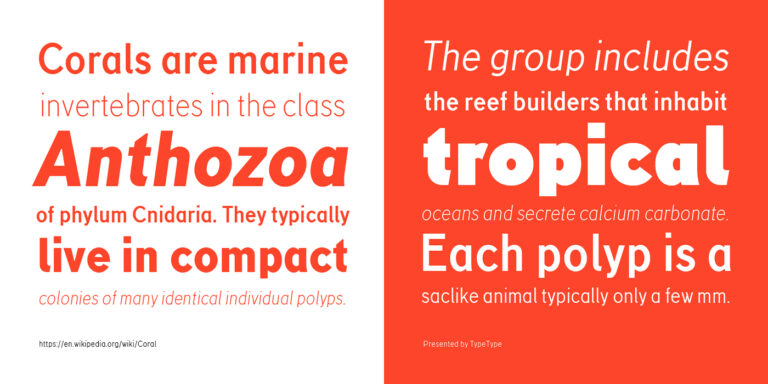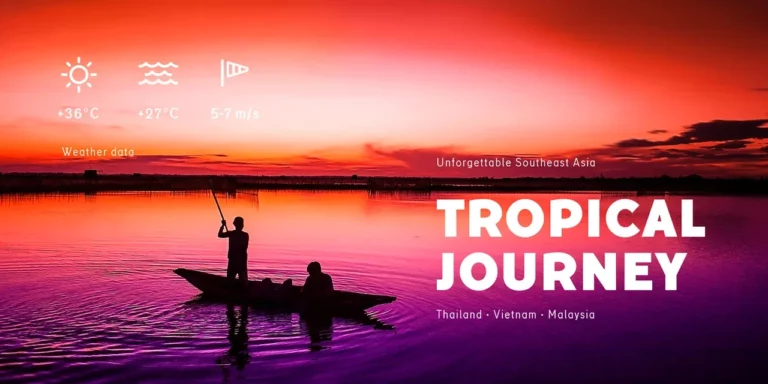
Industrielle Schriftarten
TT Hoves Pro ist eine vielseitige Sans Serif mit wiedererkennbarer Geometrie.
Wir erweitern weiterhin die Linie des wichtigsten Bestsellers unseres Studios: TT Norms® Pro!
Die Schrift TT Chocolates besteht aus 14 Fonts: 7 Strichstärken und 7 Obliques. Sie bietet erweiterte Sprachunterstützung und nützliche Features.
TT Supermolot Neue ist eine neu gestaltete, erweiterte und deutlich verbesserte Reinkarnation der beliebten Schriftfamilie.
TT Rationalist ist eine funktionale und neutrale Slab-Serif-Schrift.
TT Turns ist eine markante geometrische Sans Serif mit expressiven Elementen. Diese vielseitige Schrift eignet sich hervorragend für Fließtext und entwickelt in großen Schriftgraden einen ausgeprägten Display-Charakter.
TT Firs Neue ist eine zeitgemäße Reinkarnation der guten alten serifenlosen TT Firs.
TT Fors ist eine moderne geometrische Sans Serif mit Zeichen und Formen, die sich in ihrer Breite kontrastreich unterscheiden.
TT Fellows ist eine humanistische Sans Serif mit mechanischer Anmutung.
TT Biersal ist eine Display-Sans-Serif mit freigeistigem, verspieltem und abenteuerlustigem Charakter. Das Konzept dieser Schrift wurde von einem deutschen Plakat aus den frühen 1930er-Jahren inspiriert.
TT Paplane ist eine kantig wirkende Display-Sans-Serif.
TT Octosquares ist eine frische, überarbeitete, erweiterte und deutlich verbesserte Version unserer ersten kommerziellen Schrift TT Squares und ihrer schmalen Variante.
TT Travels Text ist eine geometrische Grotesk mit breiten Proportionen sowie charakteristischen Kreis- und Rundungsformen und umfasst zwei stilistische Sets mit völlig unterschiedlichem Charakter.
TT Carvist ist eigenwillig, verspielt und mutig — eine Schrift, die Aufmerksamkeit hervorragend auf sich zieht.
Eine technologische Schriftfamilie für Game Design.
TT Bluescreens ist eine verbesserte geometrische Sans Serif mit schmalen Proportionen.
TT Rounds Neue ist eine weiche, freundliche und abgerundete Sans-Serif-Schriftfamilie.
TT Smalls ist heute eine dekorative Schrift, mit der sich Aufmerksamkeit ganz leicht erzeugen lässt.
TT Autonomous ist eine moderne Techno-Grotesk mit breiten, kantigen Proportionen.
TT Backwards Sans ist eine schmale Grotesk, deren geschmeidige Zeichenformen an Buchgestaltung der späten 1970er- und frühen 1980er-Jahre erinnern.
TT Polls ist eine moderne modulare Slab-Serif-Familie für den Einsatz im Sportdesign.
TT Corals ist eine moderne humanistische Sans Serif mit vielen typischen Merkmalen des frühen 20. Jahrhunderts. Für eine höhere Funktionalität der Schriftfamilie haben wir sechs Schnitte mit unterschiedlichen Strichstärken entwickelt.
TT Slabs ist eine Slab Serif, auch Egyptienne oder Square Serif genannt. Schriften dieser Art entstanden kurz nach der Industriellen Revolution um 1850, als die Werbebranche zu wachsen begann.